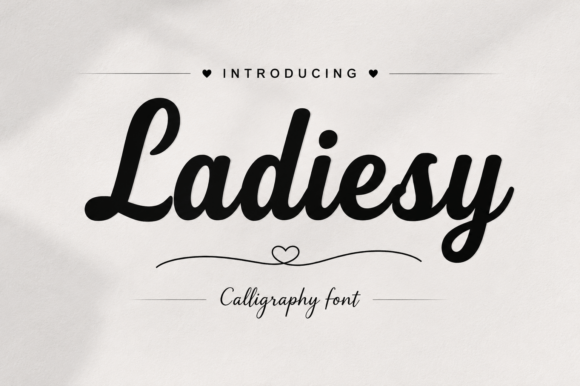
Ladiesy
Wenn Sie nach hochwertigen Assets wie Ladiesy suchen, ist dieses Premium-Paket eine fantastische Wahl für Ihre kreativen Projekte.
Egal, ob Sie POD-Produkte (Print on Demand), Hochzeitseinladungen oder Social-Media-Grafiken erstellen, Ladiesy ist die ideale Wahl.